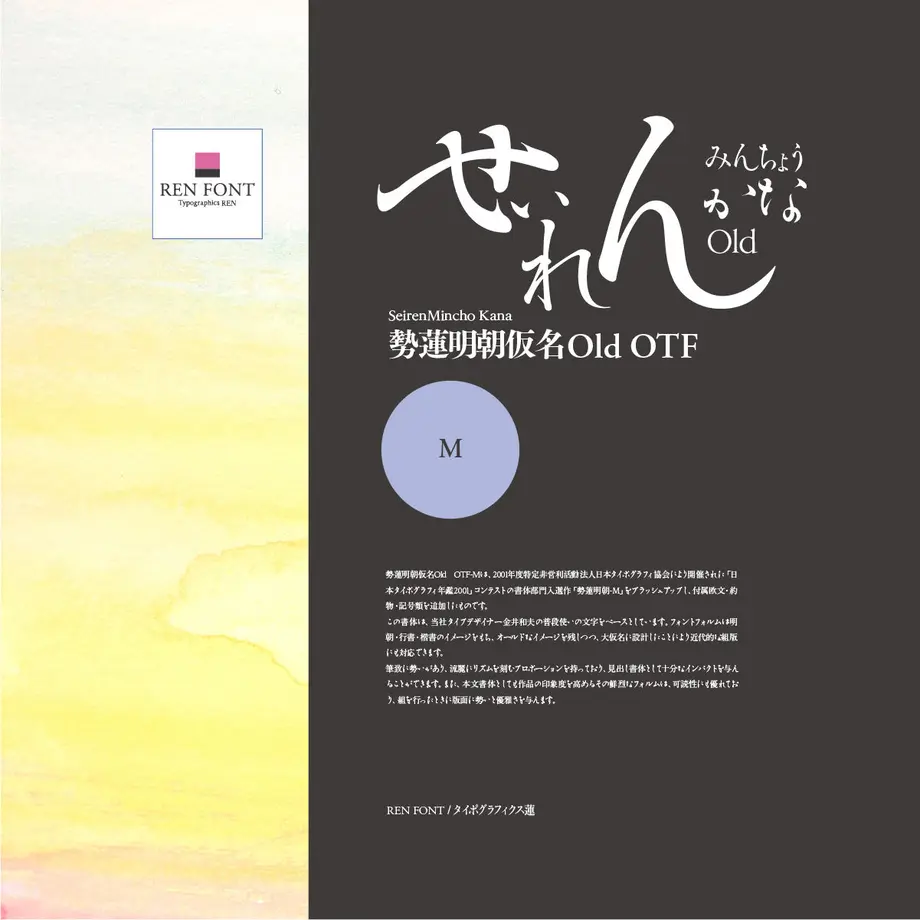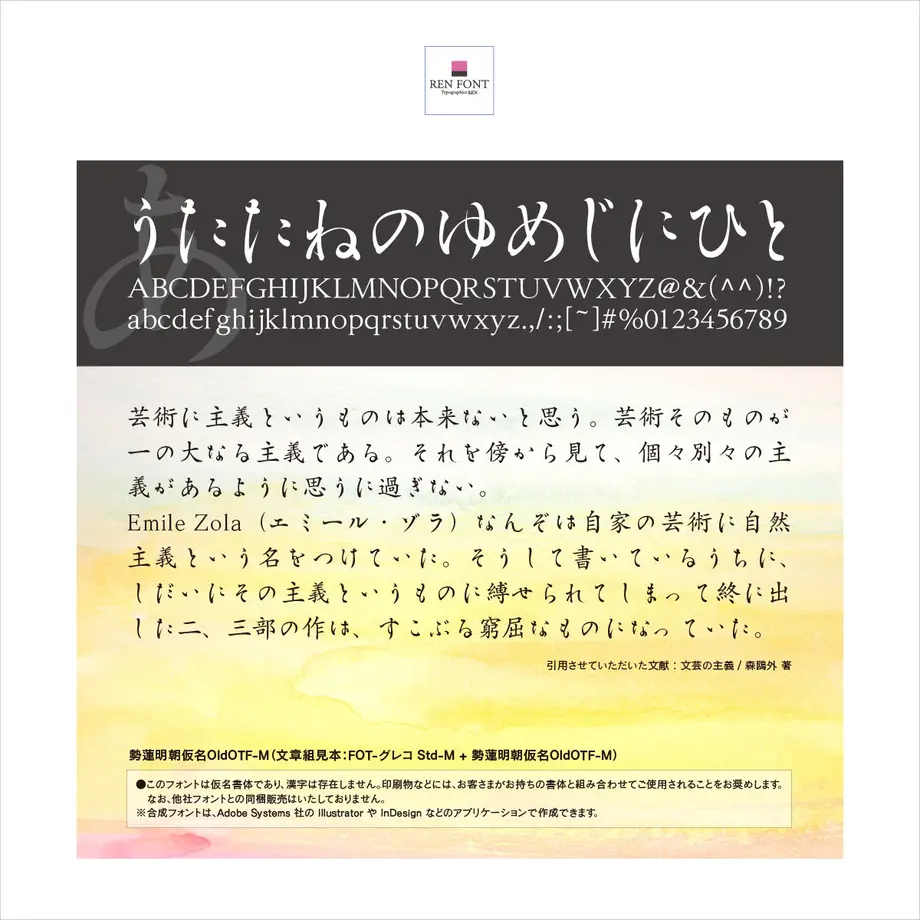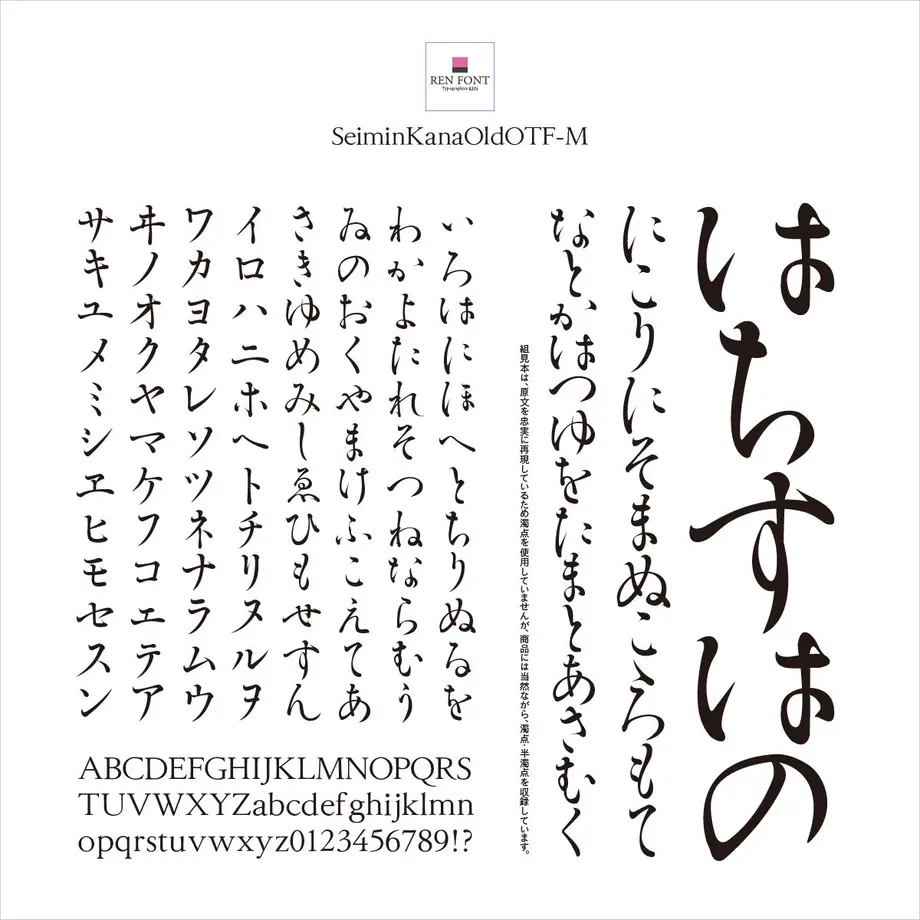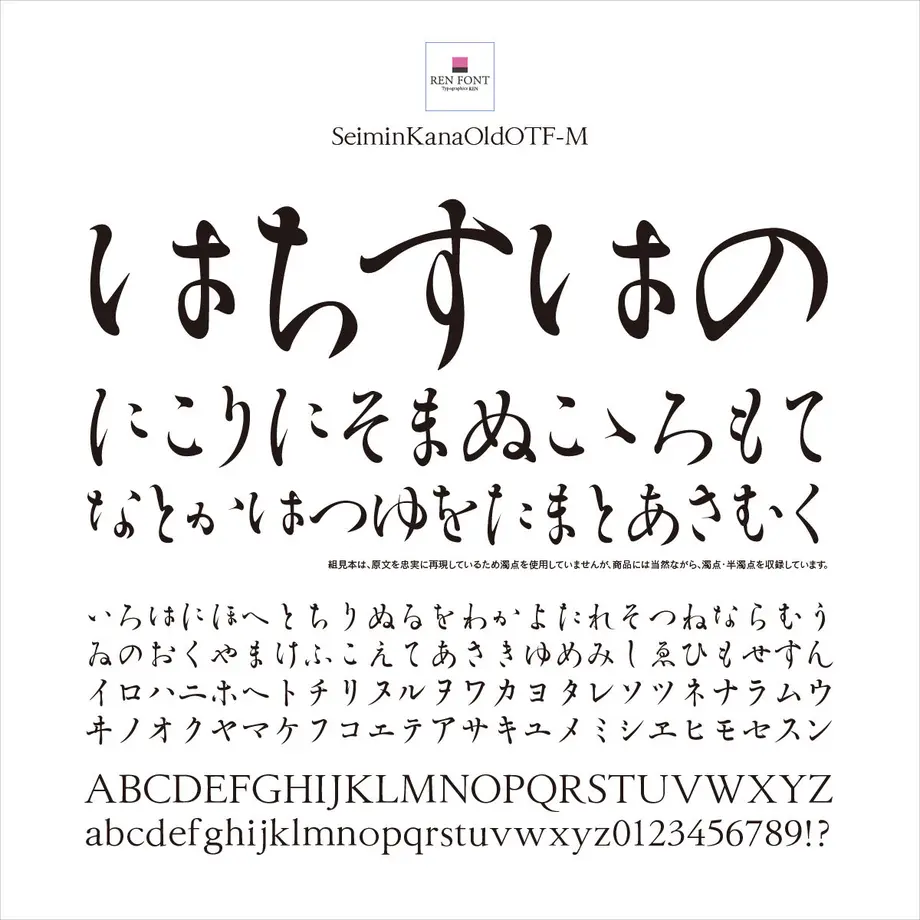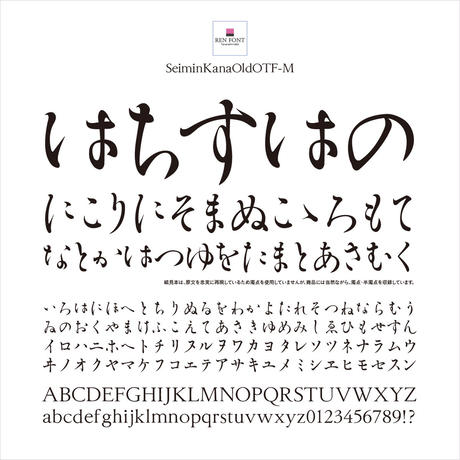
徹底して手書き風にこだわった
勢蓮明朝仮名Old-M / OpenType
勢蓮明朝仮名Old OTF-Mは、2001年度特定非営利活動法人日本タイポグラフィ協会により開催された「日本タイポグラフィ年鑑2001」コンテストの書体部門入選作「勢蓮明朝-M」をブラッシュアップし、付属欧文・約物・記号類を追加したものです。
この書体は、当社タイプデザイナー金井和夫の普段使いの文字をベースとしています。フォントフォルムは明朝・行書・楷書のイメージをもち、オールドなイメージを残しつつ、大仮名に設計したことにより近代的な組版にも対応できます。
筆致に勢いがあり、流麗にリズムを刻むプロポーションを持っており、見出し書体として十分なインパクトを与えることができます。また、本文書体としても作品の印象度を高めるその鮮烈なフォルムは、可読性にも優れており、組を行ったときに版面に勢いと優雅さを与えます。
明朝体の形状を基本にしていますが、行書・楷書のイメージも含んでいます。
作者の普段使いの文字をアレンジしてあるので、明朝のセオリーを外した筆勢も随所にあり、強い個性と主張を発揮します。
起筆や払い、跳ねの細い先端は、丸く処理してあり、ソフトさもさりげなく持ち合わせています。
文字の高さや横幅がフォントの概念を覆すほどバラエティに富んでいるので、一文字ずつばらしてサイズに強弱をつけると、見出しとしてあたかも書道のような最大限の効果を得られます。
また、本文組にも既存の漢字と組み合わせてよく調和します。
欧文・数字は、特徴の強い両仮名に合わせて独自にデザインしました。
格調高いGaramondに近い形状をもっていますが、手書きの風合いを出すために、エクスハイトを高めに設定したり、セリフを短めにして、あえてアンバランスさを強調しています。